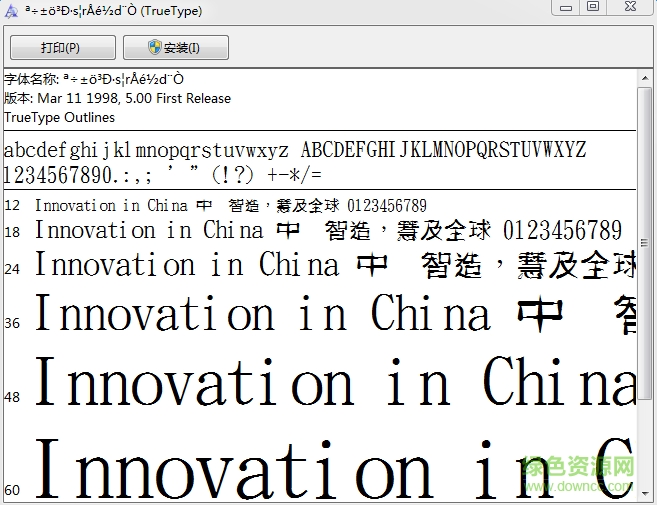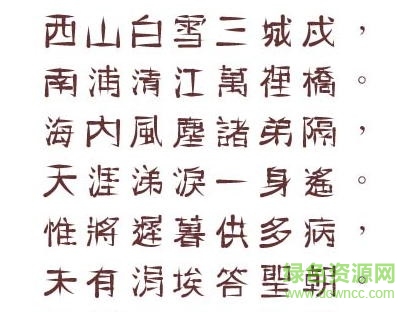
金梅創(chuàng)新字體是金梅字體的一種繁體字體,雖說(shuō)是繁體字,但是卻沒(méi)有那么難懂,寫(xiě)出來(lái)的字倒是有點(diǎn)像鋼筆寫(xiě)出來(lái)的字,有點(diǎn)細(xì),但是很均勻,很合適,有需要的朋友可以來(lái)綠色資源網(wǎng)下載。
好看的美工設(shè)計(jì)字體,該字體圓潤(rùn)研究,看起來(lái)頗具正式之感,不過(guò)個(gè)性之處在于每個(gè)字都有一個(gè)大小眼的圖案,整體上非常的特別。